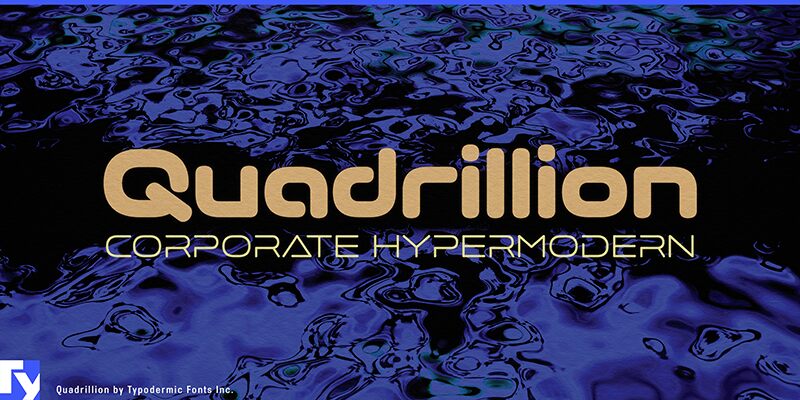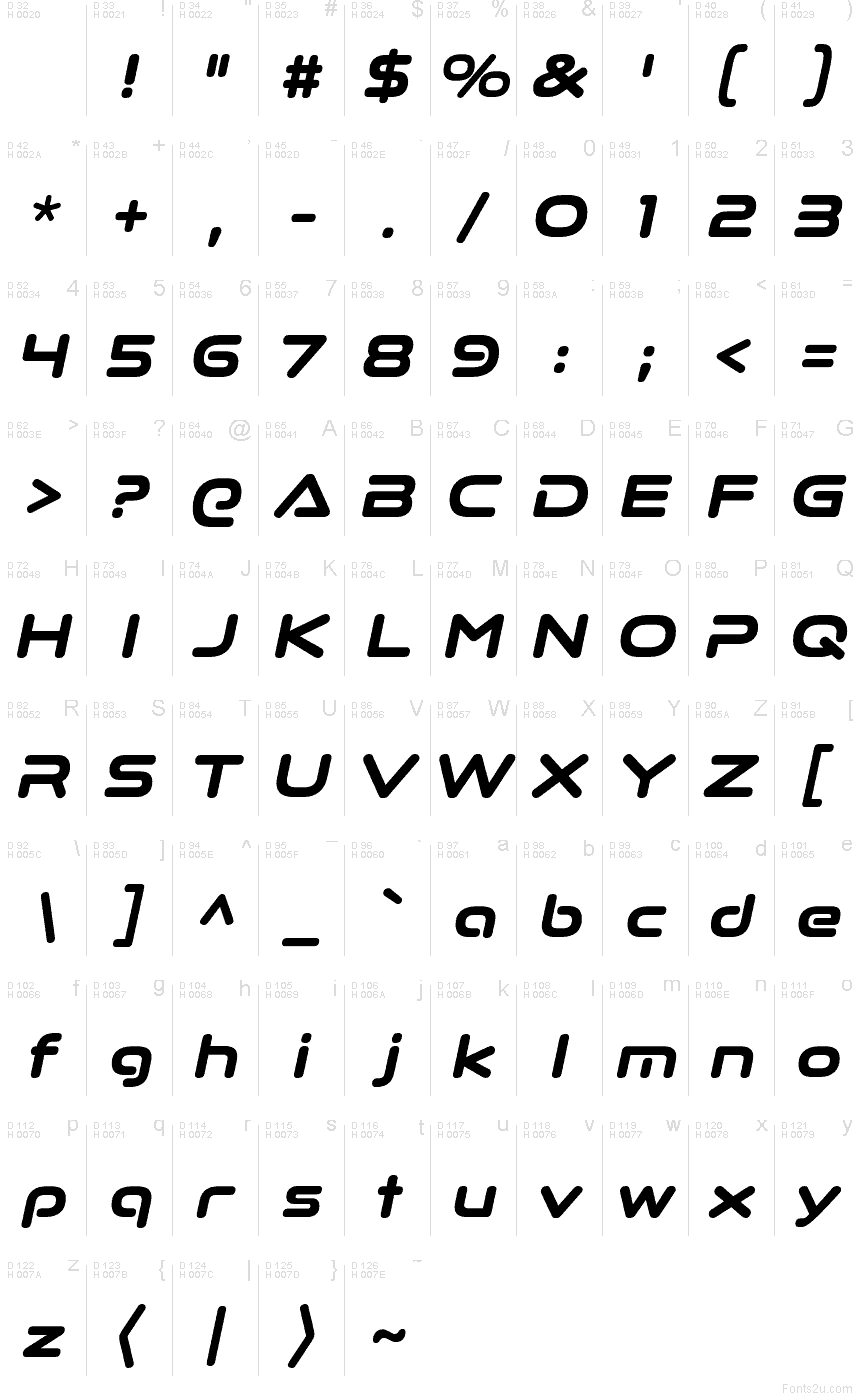
Quadrillion Semi Bold to szeroki, futurystyczny krój bezszeryfowy o kapsułowych formach i zaokrąglonych końcówkach. Zrównoważona geometria i hojne odstępy nadają mu płynny, pewny rytm, który wyróżnia się w nagłówkach, zachowując przy tym przejrzystość w nowoczesnym brandingu i projektach wydawniczych.
Design łączy elegancką szybkość technologicznego liternictwa z bardziej miękkim, przystępnym charakterem, dzięki czemu idealnie sprawdza się w interfejsach technicznych, opakowaniach, tytułach filmowych i innych nowatorskich projektach. Dzięki obsłudze alfabetów łacińskiego, greckiego i cyrylicy, Quadrillion z łatwością adaptuje się do globalnych prac projektowych.